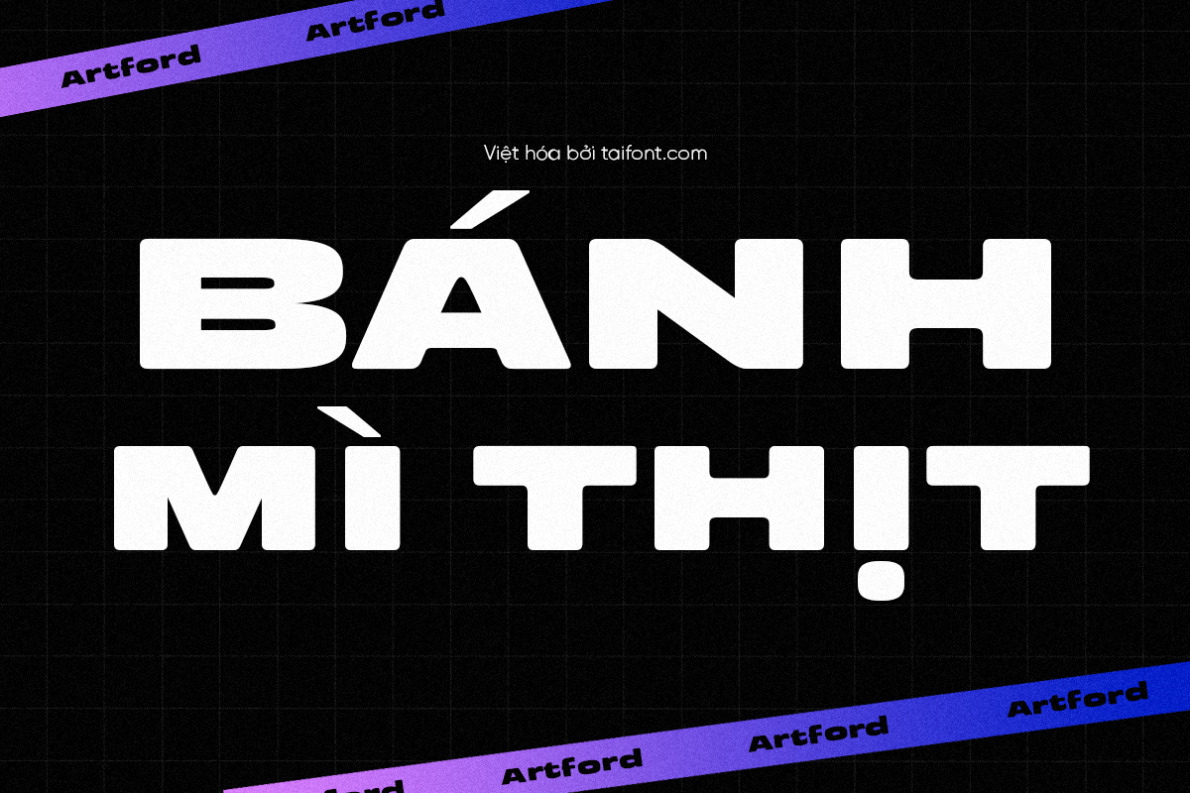
Font Việt Hóa Dafont Đẹp Cho Thiết Kế
Font Việt Hóa Dafont Đẹp Cho Thiết Kế. Đây là 5 font chữ được lựa chọn từ dafont để Việt hóa.
Trong thế giới thiết kế đồ họa, việc lựa chọn font chữ phù hợp là rất quan trọng để tạo nên sự hài hòa và ấn tượng. Dưới đây là 5 font chữ Việt hóa đẹp, được nhiều designer yêu thích, giúp bạn nâng cao chất lượng thiết kế của mình. Font Việt hóa dafont sẽ là lựa chọn tuyệt vời.
1. Font Achemost
Font Achemost có nhân nét đậm, tạo nên sự nổi bật và thu hút. Với phong cách mạnh mẽ, font này rất phù hợp cho thiết kế tiêu đề, tạo ấn tượng ngay từ cái nhìn đầu tiên.
2. Font Simple Michael
Nếu bạn đang tìm kiếm một font chữ dễ thương, thì Simple Michael là lựa chọn hoàn hảo. Với các nét chữ thanh thoát và mềm mại, font này rất thích hợp cho các thiết kế thời trang, mang lại vẻ hiện đại và tươi mới.
3. Font Oakside Typeface
Với nét đậm và bo tròn, Oakside Typeface là một sự lựa chọn tuyệt vời cho các dự án liên quan đến ẩm thực. Font chữ này không chỉ bắt mắt mà còn truyền tải được sự ngon miệng và hấp dẫn cho sản phẩm.
4. Font Stagera
Font Stagera nổi bật với những đường công uốn lượn thanh thoát. Nó có nhiều Glyphs đẹp, giúp cho các thiết kế trở nên sinh động và dễ nhớ. Rất phù hợp cho các sản phẩm mang phong cách nghệ thuật.
5. Font Artford Medium
Cuối cùng, Artford Medium mang đến một phong cách hiện đại và năng động. Font chữ này lý tưởng cho các thiết kế quảng cáo và in ấn, giúp toát lên tính chuyên nghiệp và sáng tạo.